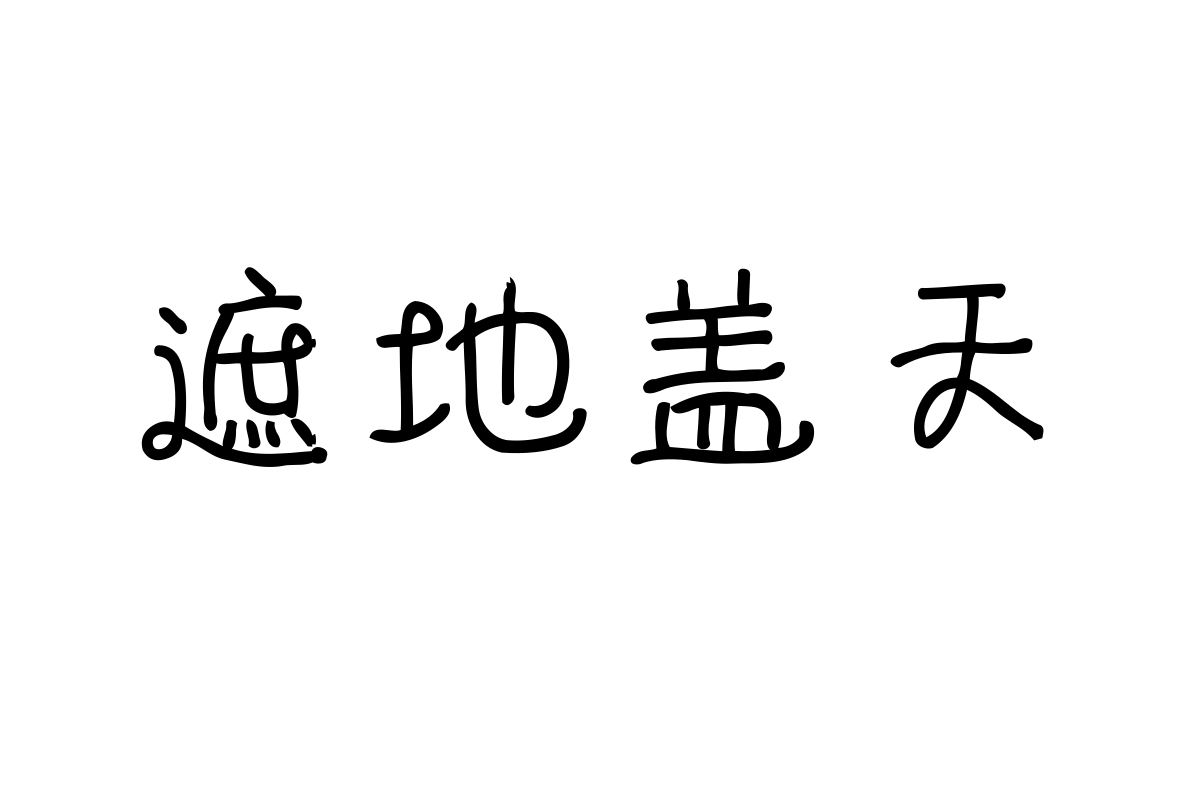
蝉羽猪猪侠の女神是一款中文字体,具有独特的设计和风格。这款字体的特点是字形流畅,线条优美,给人一种优雅而高贵的感觉。它适合用于需要表现女性气质和高雅的场合,如广告、设计、印刷等。
蝉羽猪猪侠の女神字体的特点包括:
1. 字形流畅:这款字体的字形线条优美,给人一种流畅的感觉,使得整体视觉效果更加和谐。
2. 线条优美:这款字体的线条细腻,线条之间的过渡自然,使得整体视觉效果更加美观。
3. 高贵典雅:蝉羽猪猪侠の女神字体的设计独特,线条优美,给人一种高贵而典雅的感觉,非常适合用于需要表现女性气质和高雅的场合。
4. 适用范围广泛:这款字体适用于各种场景,如广告、设计、印刷等,能够满足不同用户的需求。
总的来说,蝉羽猪猪侠の女神是一款具有独特设计风格的中文字体,适合用于需要表现女性气质和高雅的场合。